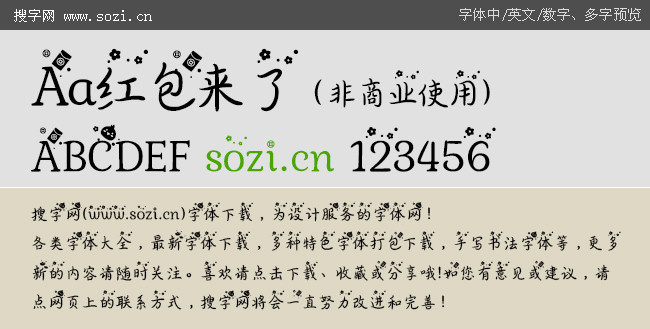
Aa紅包來了(非商業(yè)使用)
搜字網(wǎng)給大家提供一款A(yù)a紅包來了(非商業(yè)使用)中文字體下載,該字體是一款卡通中文字體,字形有趣可愛,并裝飾有卡通圖案,充滿童真,適合兒童包裝設(shè)計、書裝設(shè)計、海報設(shè)計等應(yīng)用(此字體為個人非商用版,商用可以聯(lián)系QQ:1006760504)。